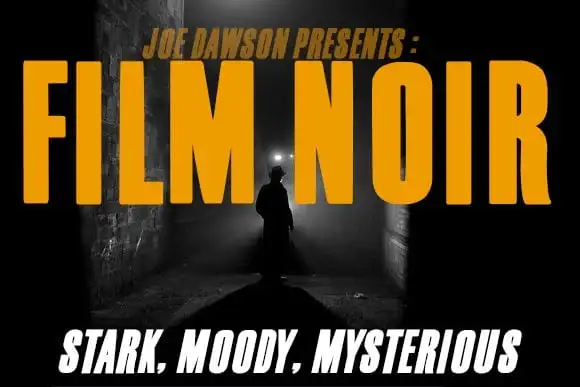
A Film Noir Sans Serif Font é uma escolha perfeita para quem busca um estilo moderno e sofisticado em suas criações. Desenvolvida cuidadosamente por especialistas na área, esta fonte sans serif oferece um contraste forte que se destaca ainda mais no design editorial ou nas marcações de logotipos femininos e fashionistas. Além disso, o seu design regular e itálico permite uma maior flexibilidade ao criar variedades distintas. A versão multilíngue da fonte traz um elemento adicional de flexibilidade para seus projetos globais ou que abrangem diversas linguagens, sem deixar de lado a qualidade. Esta font é perfeitamente adaptável tanto para t-shirts e eventos como para designs de casamentos, criações clássicas e logotipos de marca. Com sua estrutura leve e forte contraste, ela se destaca em qualquer projeto que você decida aplicá-la. E o melhor: a fonte conta com duas opções estilizadas, facilitando ainda mais o seu uso ao permitir criatividades inúmeras nas criações visuais dos seus projetos.